Y es que de esta manera podrás ocupar la tipografía de Hello Kitty en tus fiestas de cumpleaños y otros eventos temáticos.
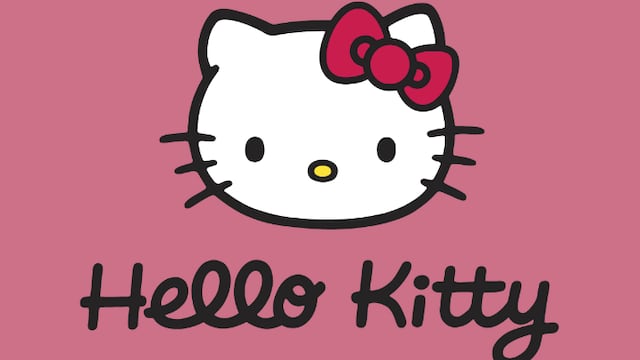
La fuente que se utiliza en el logotipo de Hello Kitty es una tipografía personalizada perteneciente a la familia Janda Happy Day de Kimberly Geswein.
Esta letra tipo cursiva de Hello Kitty, sería ideal para artículos de papelería debido a que no es pesada y es completamente legible.
Lo que a su vez la hace ideal para utilizarse en invitaciones y distintos letreros que adornen las fiestas de cumpleaños temáticas.
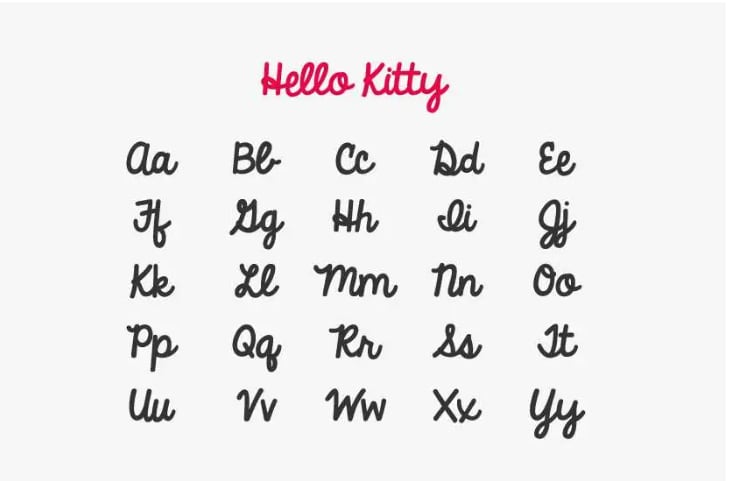
Y es que la tipografía de Hello Kitty oficial está hecha para el uso exclusivo de Sanrio, por lo que en internet no se puede encontrar una igual.